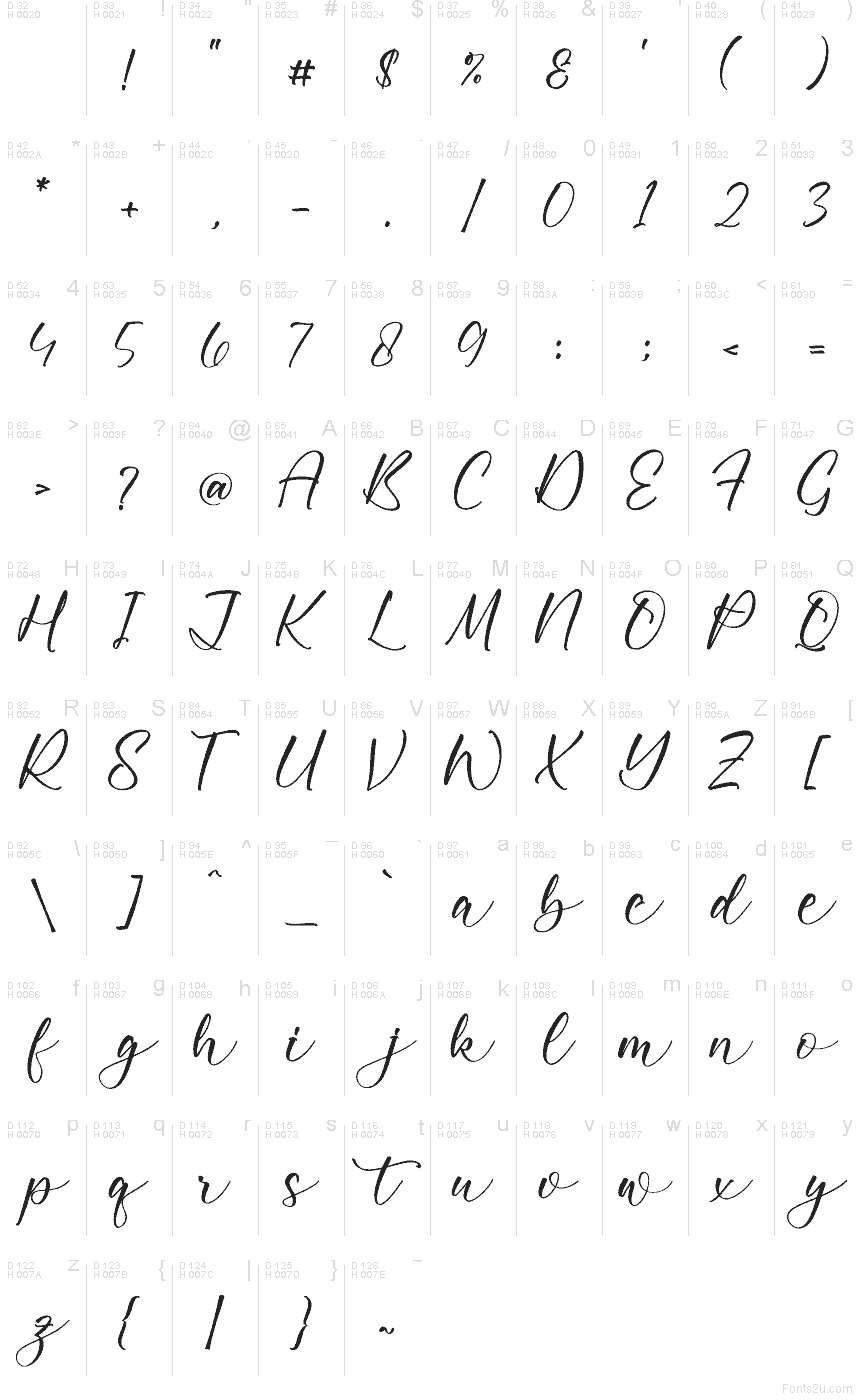
Rayetta Wegatta od Integritype Studio je bezplatné kaligrafické písmo s lehkým, vzdušným rytmem a přirozeným švihem ručně psaného textu. Písmena využívají dlouhé spojovací tahy, otevřené smyčky a několik výrazných ozdob, takže výsledný styl působí osobně, nikoliv formálně.
Skvěle se hodí na obaly kosmetiky, loga butiků, citáty na sociální sítě, svatební oznámení nebo titulky v časopisech, kde bezplatné písmo s rukopisným nádechem působí lidštěji než uhlazená typografie. Použijte jej, když chcete dodat šarm krátkým názvům, kartičkám nebo titulkům – protažené tahy dodají i krátkým slovům plynulý, autorský vzhled.